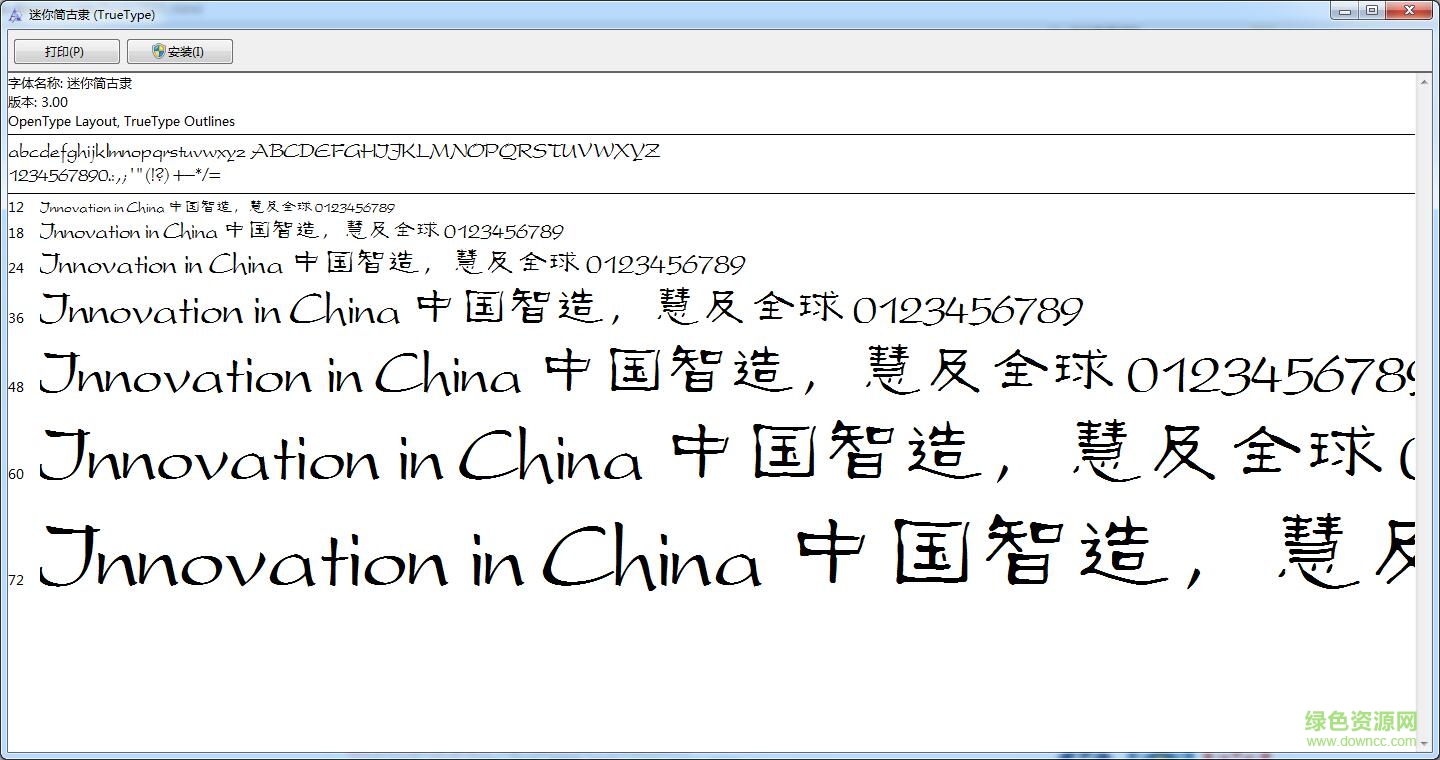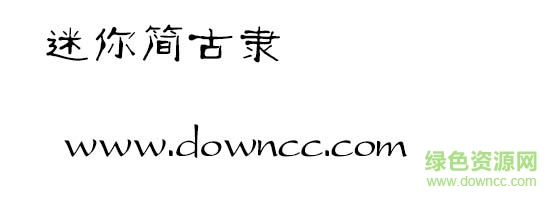
迷你簡(jiǎn)古隸字體是一款比較飄逸的字體,這款字體看起來(lái)有點(diǎn)鋼筆字的感覺,小編經(jīng)常使用!另外這種字體可以用于設(shè)計(jì)行業(yè),簡(jiǎn)單不失大氣!歡迎在綠色資源網(wǎng)下載。
迷你簡(jiǎn)古隸是在古隸字體基礎(chǔ)上開發(fā)的一款簡(jiǎn)體中文漢字,該字體線條飄逸大方,整體效果十分出色,并且字庫(kù)完整,可以適用于名片設(shè)計(jì)、平面設(shè)計(jì)、廣告設(shè)計(jì)、報(bào)紙雜志、企業(yè)LOGO、商標(biāo)注冊(cè)、電視臺(tái)廣告等領(lǐng)域!
1.靜中有動(dòng),美感十足
2.整體效果十分出色